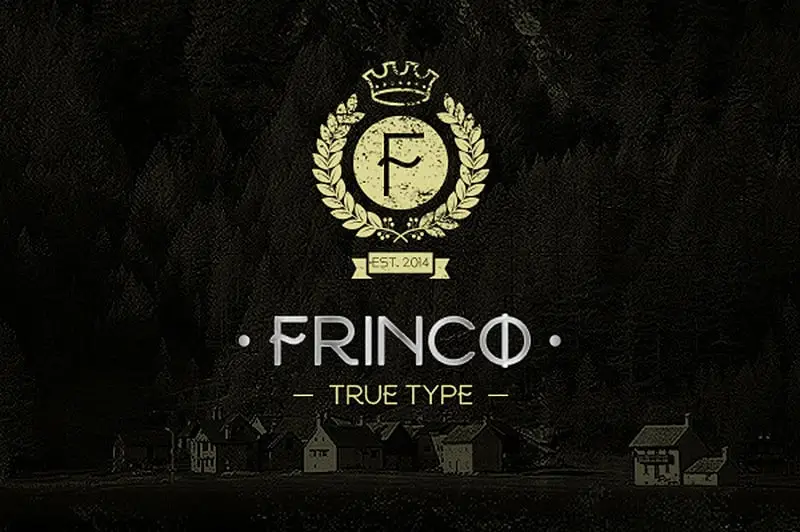
Aqui está uma descrição em português do Brasil para a página de download da fonte ‘Frinco Font’, seguindo os requisitos: Através do talento do designer Hamilton, você encontrará na Frinco Font um estilo único e criativo que se destaca no mundo das fuentes sans-serif. Com linhas finas e elegantes, essa fonte promete dar um toque moderno a qualquer projeto gráfico. Seja para o design de logotipos, materiais de marketing ou até mesmo para a criação de websites dinâmicos – Frinco pode ser usada em diversos contextos. Além disso, sua simplicidade e facilidade de uso tornam essa fonte uma escolha conveniente para designers profissionais que buscam um equilíbrio entre criatividade e praticidade no seu trabalho diário. Em breve você terá à disposição essa versão única e bem resolvida da Frinco Font, disponível tanto em formato digital quanto impresso. Descarregue-a agora e experimente o poder desta fonte inovadora!